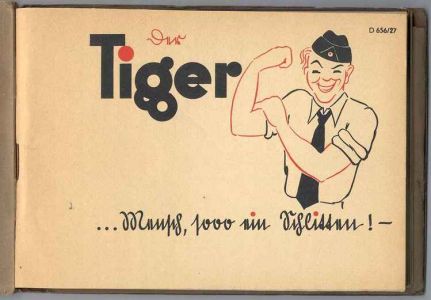
Welche Schrift ist das nur?
Ich komme einfach nicht drauf..
Habe die Schrift aus dem Wort "Tiger" schon oft gesehen bzw. das "g" daraus ist ja auch markant genug.
Kann mir da jemand helfen?
Ich habe die Antwort jemandem auf Typophile versprochen gestern, weil ich dachte, ich find's auf die Schnelle - war aber nicht so.
... vielleicht hatte ja Herr Koch was damit zu tun, dass sie Dir so gekannt vorkommt?
Also eine Kabel ist es nicht.
Und die Neuland gibt es doch nur als Versal-Schrift, oder?
Von R. Koch stammt die Schrift mit Sicherheit nicht. Die Buchstaben sind zu grade, die Schäfte nicht angeschnitten, die beiden Kringel des „g“ sind mit einem „Bügel“ verbunden, wie bei einer Brille.
Ja, die Neuland von Linotype hat nur Versalien.
Ich denke auch das die handkonstruiert ist.
Got it!
georg, bist du blind? was hat diese schrift mit der kabel zu tun? :shock:
schau mal auf die diagonalen abschrägungen am T. das g ist komplett anders, selbst mit verändern der kabel stimmt das nicht. das e hat einen diagonalen mittelstrich, das r ist auch abgeschrägt generell sieht die vorlage viel geometrischer aus. runde punzen im g, rundes r und runder i punkt. eine konstruierte schrift, warscheinlich von einem schildermaler.
das einzige was halbwegs ähnlich ist, ist die strichstärke.
Doch, bestimmt, Robert. Das ist so.
Der Typ hat das „g“ genommen und modifiziert.
Damit es an die Rollen erinnert, über die die Panzerketten befestigt sind. Aus dem Grund hat er dann auch 'nen runden „i-Punkt“ gebaut und das „T“ hochgezogen. So erinnert er an das Kanonenrohr.
Im übrigen hat mein Alter in Kursk gekämpft und 'nen Lungen-Steckschuß bekommen. Und 'nen EK I dafür bekommen. Das muß also die Kabel sein. Joh. Ich will das so.
Neither will these letters ever be Kabel!
Dafür war der Herr Hoch viel zu gut. Sorry :(
Das ist nie im Leben die Kabel!
Ich habe gerade auf Typophile auch geschrieben, dass diese Buchstaben nicht von die Kabel abgeleitet waren.
Du kannst alles über den Koch sagen was du willst, tapferkeit hin oder her! Er wird immer meinen Favorit unter den deutschen Schriftzeichnern sein… Aber seine Buchstaben haben gar nichts mit diesen hier zu tun.
Nö; Peters Mercury ist… keine Ahnung! Vielleicht den Beschreibungstext dort lesen.
Peter Bruhn selbst kommt aus Schweden, sein Vater ist aber Deutscher.
Vielleicht war das ja auch alles genau anders herum und er hat sich durch die vielen Tiger dort inspirieren lassen und daraus die Kabel entwickelt? Ach nein, geht ja nicht. Die Kabel war ja zuerst da.
PS: Dan, dies ist, bitte, mein (berüchtigter) Humor. Nicht mehr.
Ich weiß schon, daß das nicht die Kabel ist. Habe ich halt einen Fehler gemacht, egal. Es macht mir nur Spaß, das ganz nun ins Absurde zu führen.
Ich schreibe das, weil es mir oft sehr schwer fällt, auf Typophile den Humor zu verstehen und ich alles für bare Münze nehmen. Und dabei ist Dein Deutsch viel besser als mein Englisch.
ok, dann muss es doch eine variante der tanneberg sein. :twisted:
Hier noch ein Nachtrag zur „Neuland“ mit Kleinbuchstaben: Die Schrift heißt „Bride of the Monster“ und ist als Paket mit 6 Schnitten erhältlich (normal, alternatives a und g / Inline, alternatives a und g, Stencil, alternatives a ung g).